오늘은 악필탈출을 위한 글씨교정과 글씨 변화의 구성요소 그리고 글씨의 진화 등에 대한 이야기를 풀어내고, 그간 문화센터를 통해서 강의한 필봉체 강의일정표를 공유합니다.
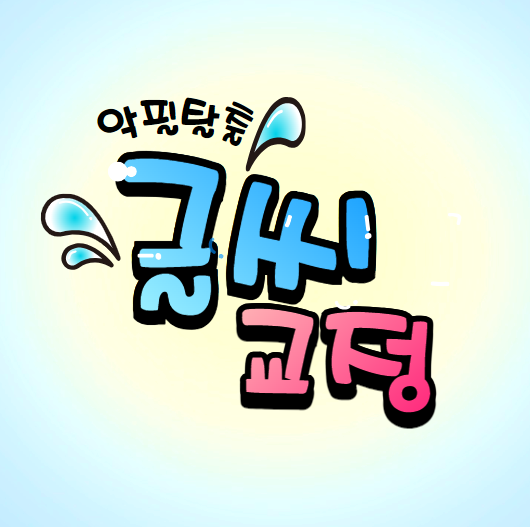
글씨 교정에 대한 생각
타고난 감각을 가진 명필이 아니라면 논리적 접근으로 글자의 구성 원리를 먼저 체득한 뒤, 바른 글씨에서 아름다운 글씨인 캘리그라피 영역, 즉 예술까지 도전해 보자!!
습자 시간의 부족과 잘못된 글쓰기 습관에 의하여 고착된 본인의 글씨에 대한 고민의 시간을 가져보자 !
본인의 글씨에 만족하지 못한 이유는 어디에 있는지 스스로 분석하여, 그간 학습해보지 않은 글씨 구성의 간단한 규칙과 의미에 대한 공부를 통하여 글씨 세계로의 소중한 여행을 해보자 !본인만의 멋지고 개성미 넘치는 글씨를 완성하여...
글씨에 대한 자신감을 갖도록 하자 !
자신감은 스스로를 귀히 여기는 자존감에서 나온다.
처음부터 잘 쓰려는 조바심을 버리고 담담하게 기본을 학습하여 스스로의 두뇌와 근육을 훈련시켜 바른 글씨에 습관이 될 수 있도록 노력하여 완전히 체득하자 !글씨 변화의 구성요소
집필법 → 공책의 각도 → 세로획(엄지/검지)의 방향 → 필기구 선택글씨의 진화
소통(가독성) → 디자인(균형/조화)적 요소 가미 → 서법(書法) → 서예(書藝) → 서도(書道)아래는 이후 본 블로그에 게재될 필봉샘의 글씨교정 강의 일정표입니다.